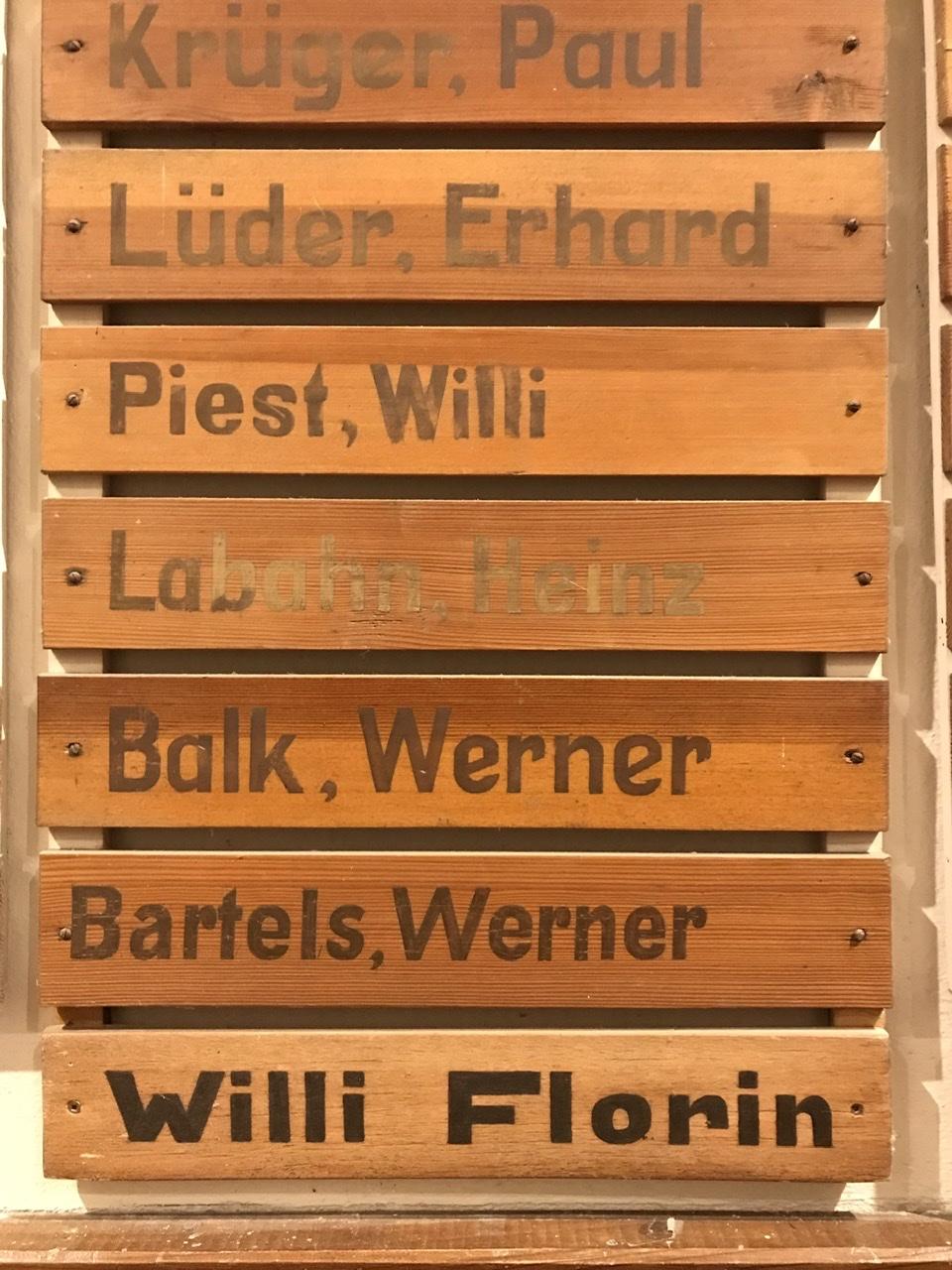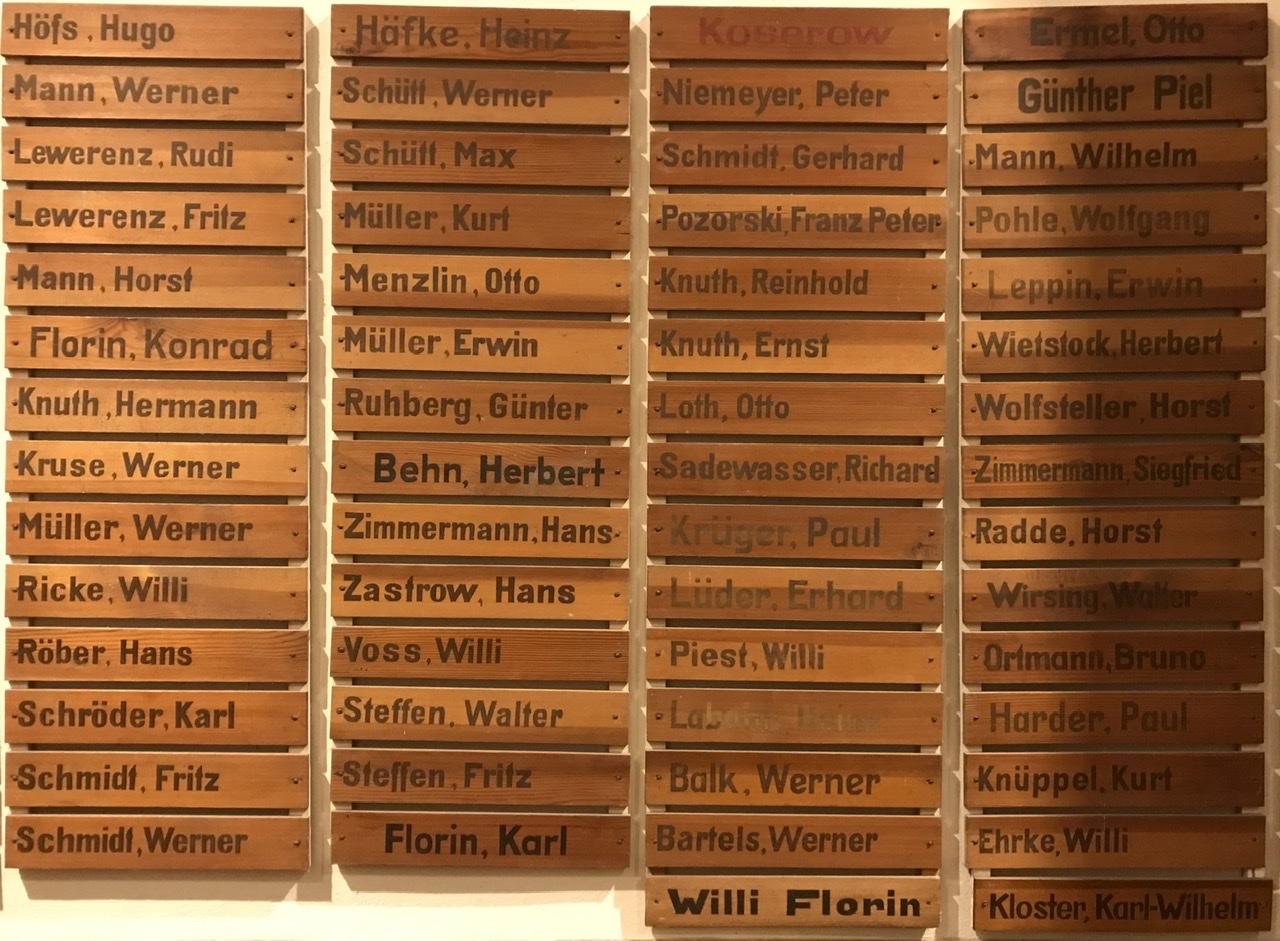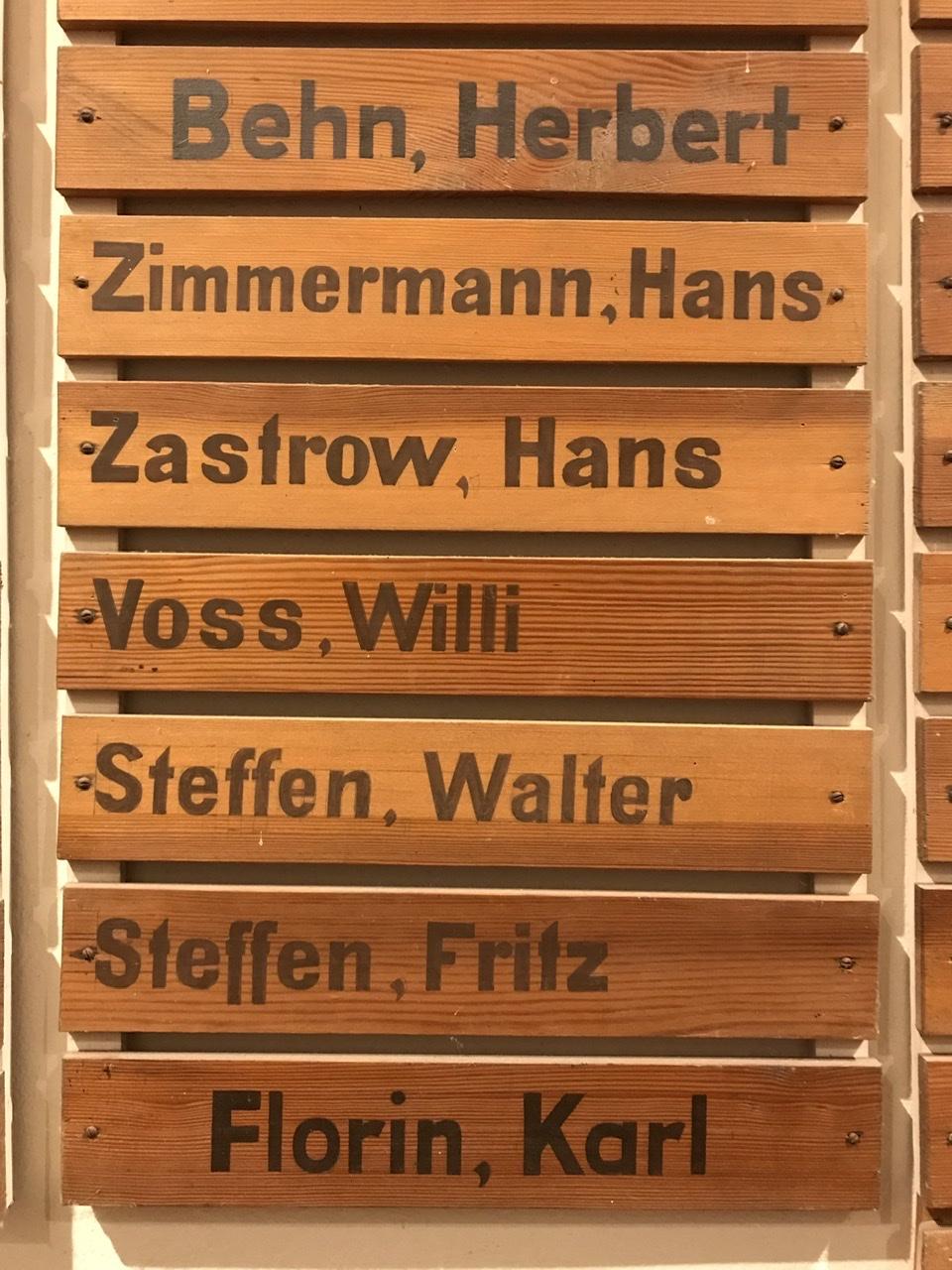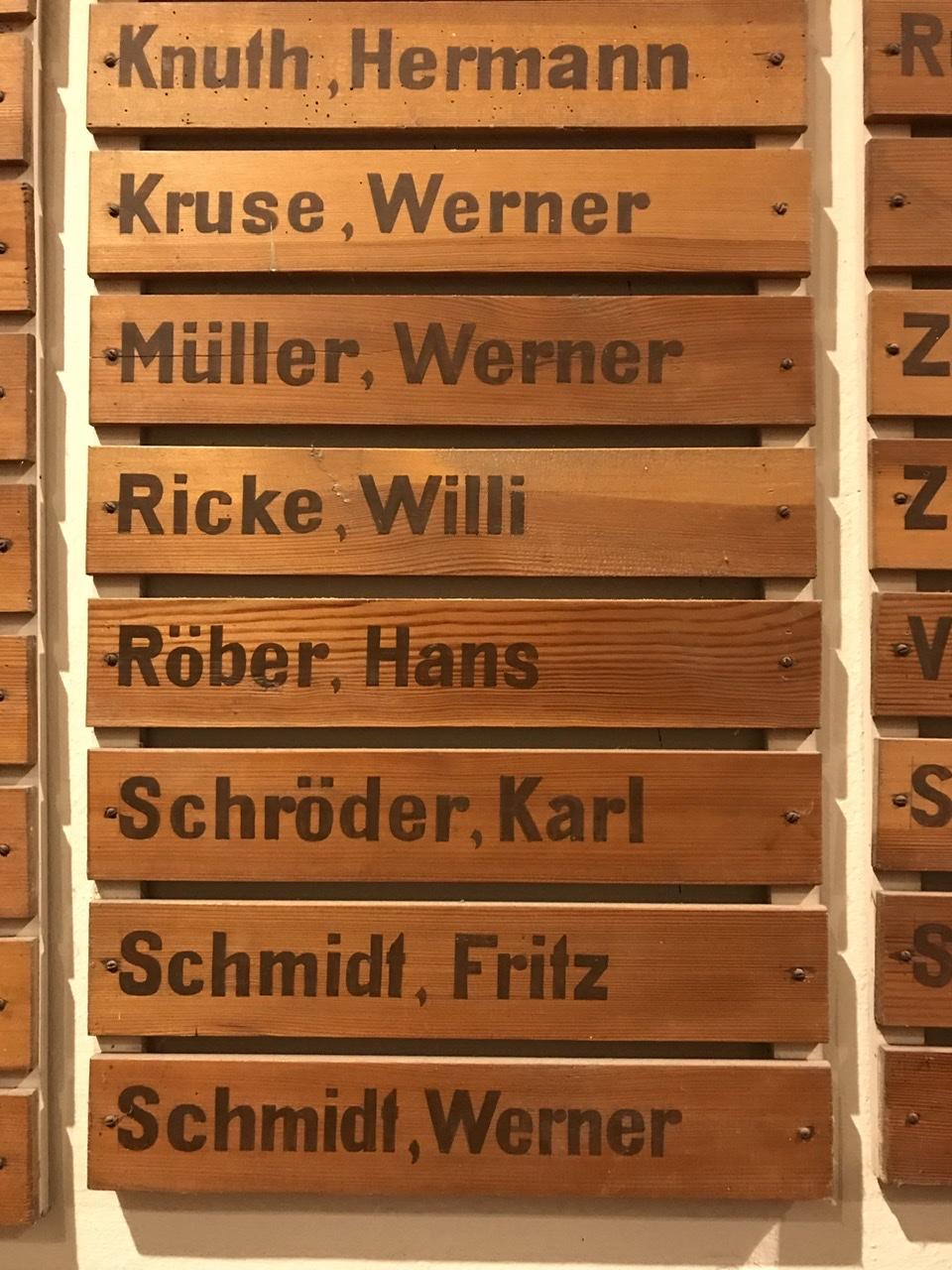
Namensschilder für Gefallene in einer kleinen Dorfkirche ...
Das sind viel zu viele! :-(
Ich finde vor allem die Methode verstörend. Statt einer Gedenktafel mit den Namen aller Kriegstoten für jeden ein kleines Schildchen. Anscheinend weil: das werden sicher noch mehr.
Wahrscheinlich wurde mit den Schildern begonnen als das ganze Ausmaß des zweiten Weltkrieges noch nicht absehbar war. 1939 zu sagen »Lasst uns lieber mal warten bis der Krieg vorbei ist und dann machen wir eine hübsche Gedenktafel« klingt für mich verstörender ...
Wenn ich mal wieder zur Familie Labahn komme - also wenn deren PC mal wieder streikt - werde ich mal fragen. Der hatte mir mämlich beiläufig erzählt, dass sein Vater im Krieg gefallen war. War aber schon länger nicht mehr in Koserow.
Da hab ich auch noch was formal ähnliches, aus unserm Kiez … der Gedanke kommt mir auch immer, wenn ich da vorbei komme: https://de.wikipedia.org/wiki/Kaiser-Wilhelm-Platz_(Berlin-Schöneberg)#/media/Datei:Berlin_-_Kaiser-Wilhelm-Platz.jpg
Das sind viel zu viele? Und dabei sind das sicher noch nicht
alle. Hätte man warten wollen, bis alle bekannt wären, wäre
wahrscheinlich heute noch was offen.  So gesehen ist dies wohl
die bessere Lösung. Über die Ausführung lässt sich natürlich
trefflich diskutieren.  Aber   "es recht zu machen Jedermann,
ist eine Kunst, die niemand kann !"
Kann Dir nicht ganz folgen .. ?!
Was ich damit meinte, war die Tatsache, daß  der Volksbund  jedes Jahr noch
weitere, z. T. unbekannte Gefallene ausgräbt, und umbettet. Wenn auch nicht
mehr ganz viel dazu vorhanden ist. Aber immer wieder werden  auch welche  gefunden, deren Verbleib  bis dato unbekannt war.  Natürlich hat man auf
solchen  Tafeln und Steinen auch die vermerkt, deren Schicksal i.E. unbe-
kannt war. Aber daß  das überhaupt zu viele waren,  nicht nur in Kose-
row, steht doch wohl außer Zweifel. Oder?
Und ich finde gerade diese Methode mit den schlichten Holztäfelchen sehr passend, wie hier ohne jedes Patghos nur an die aus der Gemeinde herausgerissenen Menschen erinnert wird.
Gerade diese Kriegstoten-Ehrentafeln triefen oft vor Pathos und letztlich Kriegsverherrlixchung, und die Toten werden zu noblen Opfern für die gute Sache hoch stilisiert. Diese einfachen Holztäfelchen hingegen zeigen nur das einzig wichtige: Menschen, die eine Lücke hinterlassen haben.
Im Gegensatz habe ich da das hamburger Kriegsgräber Ehrenmal vor Augen, mit dem Heinrich Lersch Zitat aus dem Soldatenabschied. Dieser Text hat mich schon als Schüler irritiert.
Wenn »die gute Sache« jetzt noch in Anführungsstrichen gesetzt wäre, wären wir doch endlich mal einer Meinung – unglaublich aber war :nicken::hammer: